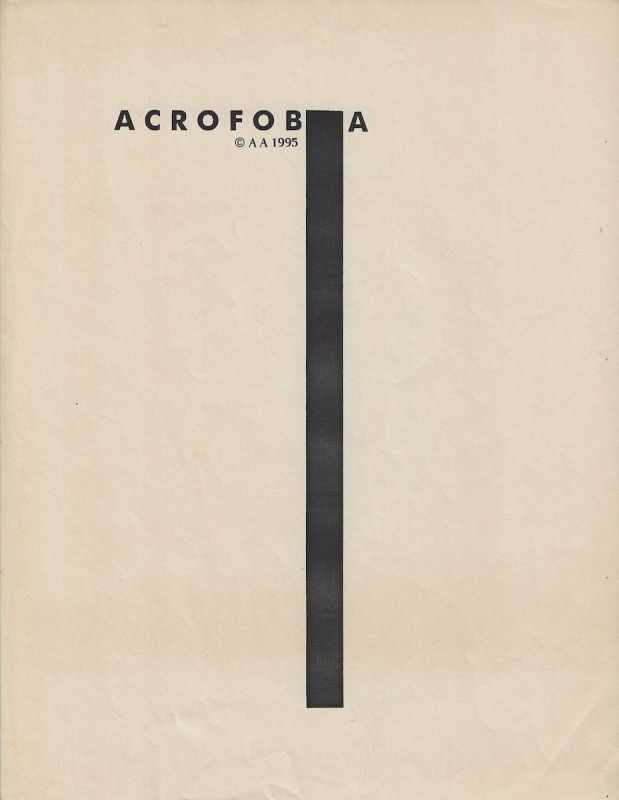
Acrofobia é uma impressão gráfica de Avelino de Araújo realizada em 1995, vinculada à poesia visual, à poesia experimental, à arte conceitual, à tipografia e às investigações intersígnicas relacionadas ao campo do Poema Processo.
Acrofobia é uma impressão gráfica de Avelino de Araújo realizada em 1995, vinculada à poesia visual, à poesia experimental, à arte conceitual, à tipografia e às investigações intersígnicas relacionadas ao campo do Poema Processo. A composição apresenta a palavra ACROFOBIA em letras maiúsculas negras e amplamente espaçadas na região superior da folha. Uma longa barra vertical preta desce a partir da área correspondente à letra I e ocupa grande parte do espaço central, criando uma estrutura semelhante a torre, edifício, precipício, eixo, coluna ou queda. O título designa o medo intenso de altura e orienta a interpretação da relação entre palavra, posição e dimensão. Avelino de Araújo transforma a linguagem verbal em experiência espacial. A palavra permanece na parte elevada da página, enquanto a barra negra prolonga verticalmente a sensação de altura e conduz o olhar para baixo. O observador não apenas lê o termo acrofobia, mas percebe visualmente a distância, a extensão e o risco sugeridos pelo medo de lugares altos. A letra I parece crescer de maneira desproporcional ou converter se em uma estrutura arquitetônica, fazendo com que o próprio signo participe do significado da obra. A linha vertical também pode ser compreendida como queda interrompida, abismo gráfico, coluna sem apoio, medidor de altitude ou fronteira entre dois lados vazios. O amplo espaço claro ao redor intensifica a sensação de isolamento, vertigem, silêncio e vulnerabilidade. A composição utiliza extrema economia de elementos e demonstra como uma única alteração tipográfica pode transformar uma palavra em imagem. A posição superior do título reforça a ideia de elevação, enquanto o prolongamento descendente produz tensão entre estar no alto e imaginar a queda. A obra investiga medo, percepção, corpo, espaço, equilíbrio, instabilidade, direção e limite. Próximo ao título aparecem a marca de autoria A A e o ano 1995. Acrofobia integra a produção de Avelino de Araújo baseada na transformação de palavras, letras, proporções e estruturas geométricas em poemas visuais de leitura imediata e reflexão conceitual. Palavras chave para indexação: Avelino de Araújo, Acrofobia, 1995, impressão gráfica, poesia visual brasileira, poema visual, poesia experimental, arte conceitual, Poema Processo, medo de altura, vertigem, queda, abismo, torre, coluna vertical, letra I, tipografia experimental, deformação tipográfica, palavra imagem, texto imagem, espaço gráfico, vazio, percepção visual, semiótica, intersigno, comunicação visual, arte gráfica brasileira, múltiplo gráfico, arquivo de poesia visual, arte brasileira do século vinte.TEXT FOR THE SALSA PROGRAM IN ENGLISH: Acrophobia is a graphic print by Avelino de Araújo produced in 1995 and associated with visual poetry, experimental poetry, conceptual art, typography and intersemiotic investigations related to the field of the Poema Processo movement. The composition presents the word ACROFOBIA in widely spaced black capital letters in the upper region of the sheet. A long black vertical bar descends from the area corresponding to the letter I and occupies a large part of the central space, creating a structure resembling a tower, building, precipice, axis, column or fall. The title refers to an intense fear of heights and guides the interpretation of the relationship among word, position and scale. Avelino de Araújo transforms verbal language into spatial experience. The word remains at the elevated part of the page, while the black bar extends the sensation of height and directs the eye downward. The viewer does not merely read the term acrophobia but visually perceives the distance, extension and risk suggested by fear of high places. The letter I appears to grow disproportionately or transform into an architectural structure, causing the sign itself to participate in the meaning of the work. The vertical line may also be understood as an interrupted fall, graphic abyss, unsupported column, altitude indicator or boundary between two empty fields. The broad light space surrounding the image intensifies sensations of isolation, vertigo, silence and vulnerability. The composition uses an extreme economy of elements and demonstrates how a single typographic alteration can transform a word into an image. The upper position of the title reinforces the idea of elevation, while the downward extension creates tension between being high above and imagining a fall. The work investigates fear, perception, the body, space, balance, instability, direction and limits. The authorship mark A A and the year 1995 appear near the title. Acrophobia belongs to Avelino de Araújo
s production based on transforming words, letters, proportions and geometric structures into visual poems with immediate recognition and conceptual depth. Keywords for indexing: Avelino de Araújo, Acrophobia, Acrofobia, 1995, graphic print, Brazilian visual poetry, visual poem, experimental poetry, conceptual art, Poema Processo, fear of heights, height, vertigo, fall, abyss, tower, vertical column, letter I, experimental typography, typographic deformation, word image, text image, graphic space, emptiness, visual perception, semiotics, intersign, visual communication, Brazilian graphic art, graphic multiple, visual poetry archive, twentieth century Brazilian art.
Impressão gráfica em tinta preta sobre papel claro de tonalidade levemente amarelada. A composição ocupa principalmente a parte superior e central da folha. A palavra ACROFOBIA aparece em letras maiúsculas, com amplo espaçamento entre os caracteres. Uma barra retangular preta, estreita e muito longa, parte da região central da palavra e desce verticalmente até próximo da parte inferior da folha. A estrutura pode ser percebida como prolongamento da letra I ou como forma independente integrada ao título. O contraste entre a barra negra e o amplo campo claro produz forte sensação de altura, isolamento e profundidade. A maior parte da folha permanece sem outros elementos impressos. A marca de autoria A A e o ano 1995 aparecem abaixo da palavra, próximos ao início da barra vertical. O suporte apresenta ondulações, vincos, alterações de tonalidade, pequenas manchas, pontos de sujidade e sinais de envelhecimento e manuseio. A peça pode ser classificada como poema visual, impressão de artista, múltiplo gráfico, estudo tipográfico, composição geométrica e documento conceitual, sendo relevante para pesquisas sobre Avelino de Araújo, Poema Processo, poesia visual, medo, altura, vertigem, tipografia, percepção, semiótica e produção gráfica brasileira.OBSERVATION TEXT IN ENGLISH: Graphic print in black ink on light colored paper with a slightly yellowed tone. The composition occupies mainly the upper and central sections of the sheet. The word ACROFOBIA appears in capital letters with broad spacing between the characters. A narrow and very long black rectangular bar begins near the central area of the word and descends vertically toward the lower section of the sheet. The structure may be perceived as an extension of the letter I or as an independent form integrated with the title. The contrast between the black bar and the broad light field creates a strong sensation of height, isolation and depth. Most of the sheet remains free of other printed elements. The authorship mark A A and the year 1995 appear below the word near the beginning of the vertical bar. The support presents undulations, creases, changes in tone, small stains, spots and signs of aging and handling. The piece may be classified as a visual poem, artist print, graphic multiple, typographic study, geometric composition and conceptual document, making it relevant to research on Avelino de Araújo, Poema Processo, visual poetry, fear, height, vertigo, typography, perception, semiotics and Brazilian graphic production.
Acrophobia is a graphic print by Avelino de Araújo produced in 1995 and associated with visual poetry, experimental poetry, conceptual art, typography and intersemiotic investigations related to the field of the Poema Processo movement.